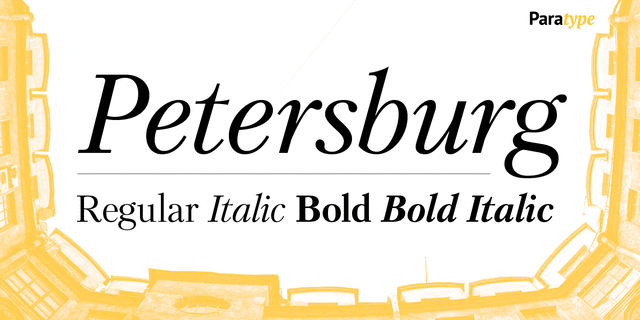
Гарнитура разработана в фирме ПараТайп (ПараГраф) в 1992 (дизайнер Владимир Ефимов) на основе рисунков гарнитуры Кудряшевская энциклопедическая НПО Полиграфмаш, 1960–74 (дизайнеры Николай Кудряшев, Зинаида Масленникова). Светлый экономичный шрифт нейтрального рисунка, он подходит как для набора длинных текстов, так и для книжных заголовков и акциденции.
Ассоциации c начертанием Petersburg BookКачества и характер:
благородный, консервативный, традиционный, классический, повествовательный, художественный, серебристый, образованный, острый, мастерский, точный, аристократичный, элитный, правильный, статичный, комильфо, пафосный, исторический, гуманитарный, серебрянный, умный